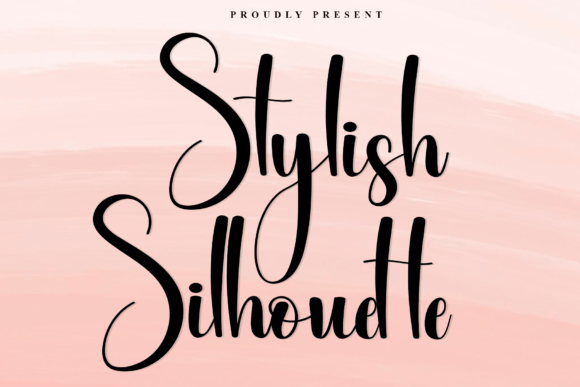
Stylish Silhouette
Stylish Silhouette – Une police d’écriture manuscrite qui respire l’élégance
Si vous cherchez une typographie qui allie modernité et raffinement, Stylish Silhouette est le choix idéal. Ce script fluide se distingue par ses courbes généreuses et ses traits allongés, offrant un rendu luxueux et authentique à chaque projet. Que vous soyez graphiste, photographe ou créateur de marques personnelles, cette police apporte une touche signature qui capte immédiatement l’attention.
Pourquoi choisir Stylish Silhouette ?
- Design élégant et fluide : chaque lettre possède une grâce naturelle qui évoque le mouvement d’une plume.
- Polyvalence professionnelle : parfaite pour le branding personnel, les filigranes de photos, les invitations de mariage haut de gamme et le design éditorial.
- Impact visuel fort : son style manuscrit confère une impression de luxe et de sophistication instantanée.
- Facile à lire : malgré son aspect artistique, la police reste claire et lisible, même en petite taille.
Utilisations idéales de Stylish Silhouette
Cette police se prête à une multitude d’applications où la témoignage d’une touche personnelle est cruciale :
- Branding & logos de créateurs indépendants
- Filigranes élégants pour les photographes professionnels
- Cartes de vœux, invitations et papeterie de mariage de luxe
- Couvertures d’ebooks, magazines et brochures haut de gamme
- Posters, affiches et supports publicitaires recherchant une signature unique
Conclusion – Le choix incontournable pour un rendu luxueux
En résumé, Stylish Silhouette est bien plus qu’une simple police manuscrite ; c’est une véritable déclaration de style. Son allure sophistiquée, combinée à une excellente lisibilité, en fait l’outil parfait pour tous les projets qui exigent une touche de luxe naturel et d’authenticité. Intégrez dès maintenant Stylish Silhouette à votre arsenal créatif et donnez à vos créations le prestige qu’elles méritent.